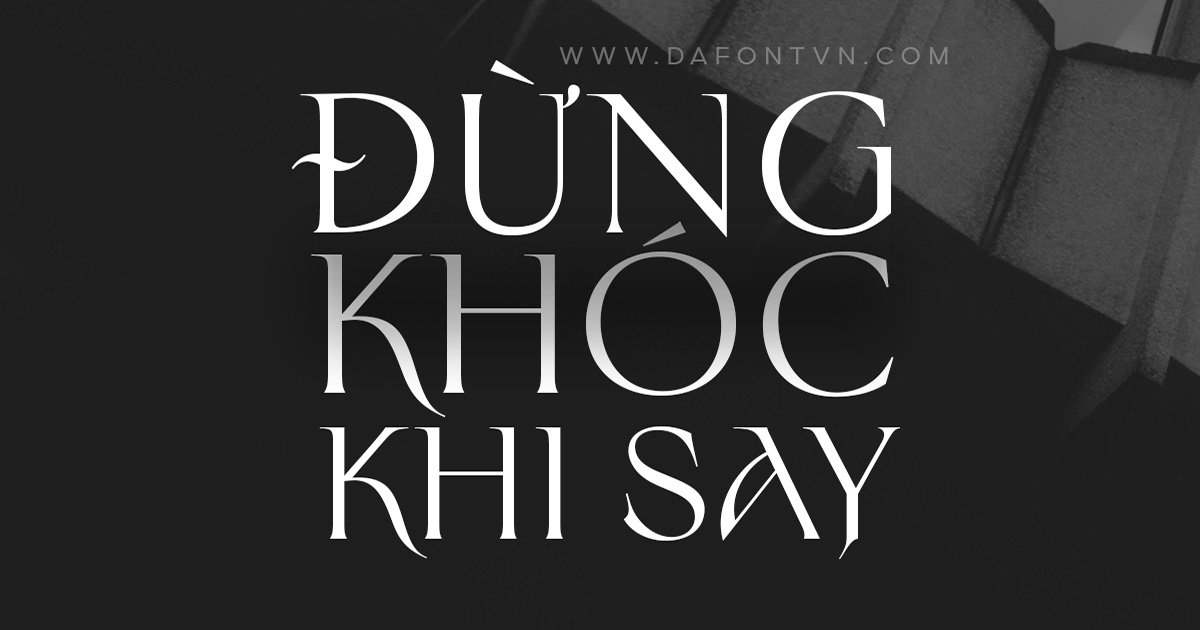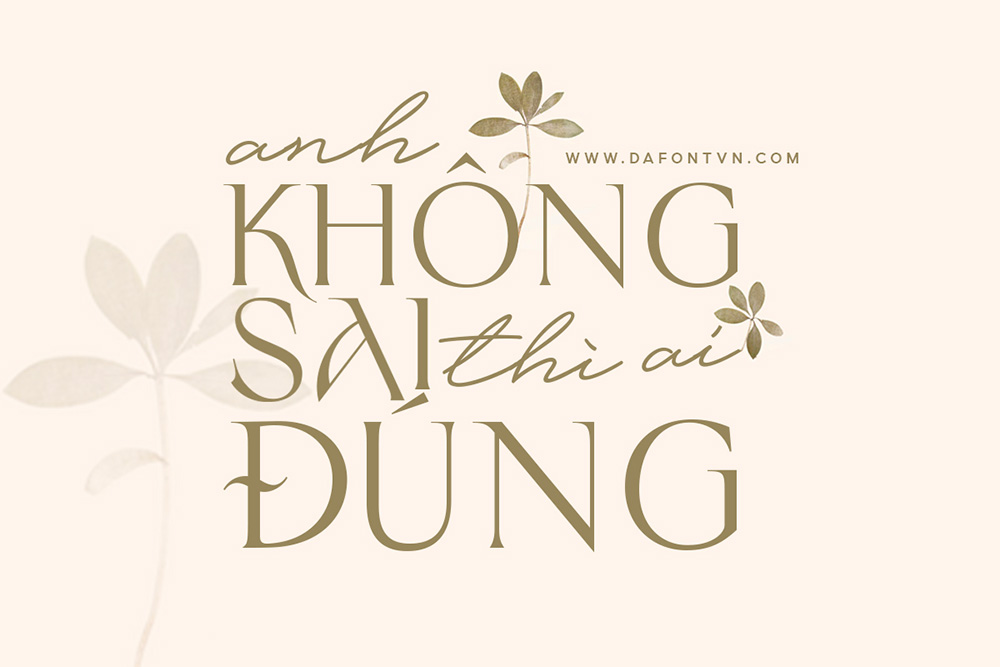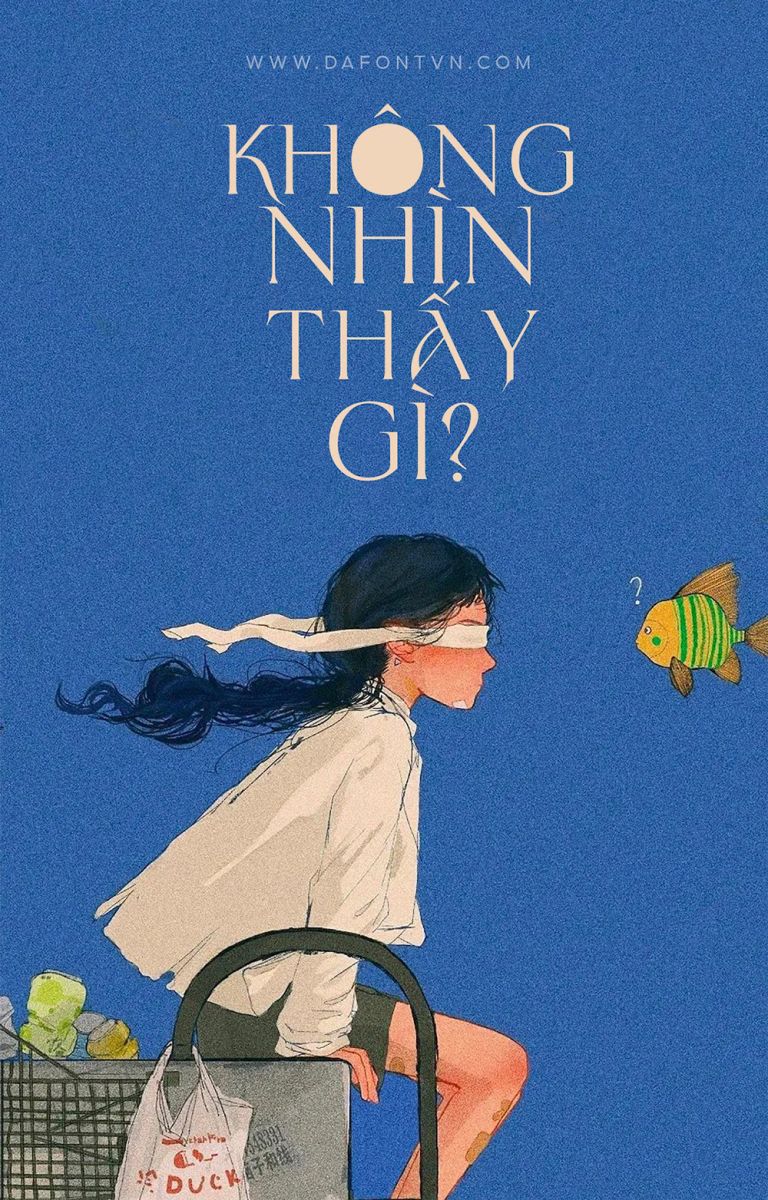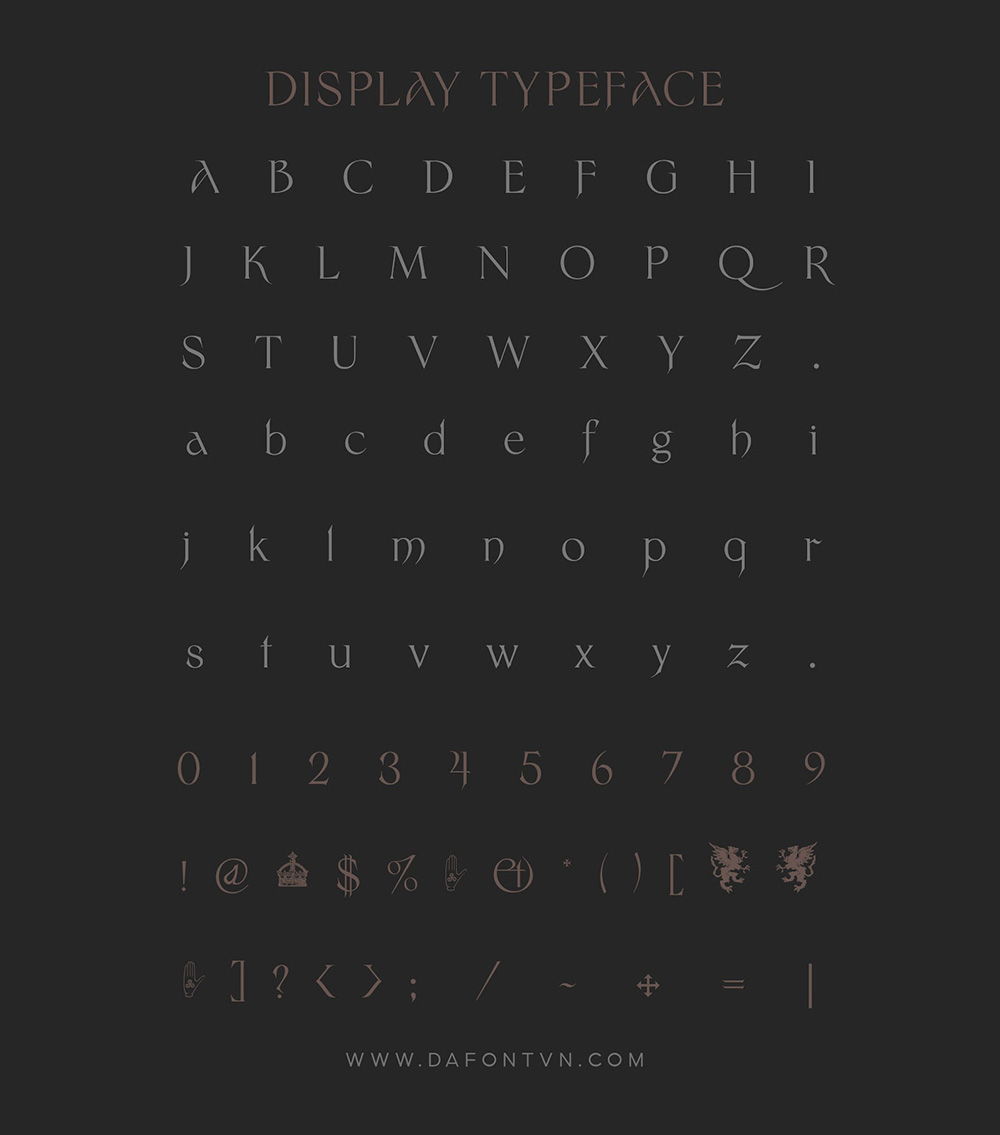
Chia Sẻ Miễn Phí Font Việt Hóa - Sinistre Cực Đẹp Mang Phong Cách Hiện Đại
Sadesign.vn vui mừng chia sẻ miễn phí font chữ Việt hóa Simple Serenity, mang đến sự kết hợp hoàn hảo giữa phong cách hiện đại và cổ điển. Được thiết kế để mang lại vẻ đẹp tối giản nhưng đầy sức hút, Simple Serenity là lựa chọn lý tưởng cho các designer yêu thích sự tinh tế và sang trọng. Với sự hỗ trợ đầy đủ các ký tự tiếng Việt, font này sẽ giúp các bạn tạo ra những sản phẩm thiết kế đẳng cấp.
1. Đặc Điểm Nổi Bật Của Font Simple Serenity
Font Simple Serenity được thiết kế với phong cách hiện đại nhưng vẫn giữ được nét cổ điển đặc trưng. Các đường nét mềm mại, thanh thoát và tỉ mỉ tạo nên một cảm giác hài hòa, dễ nhìn. Font chữ này rất phù hợp với những dự án thiết kế yêu cầu sự tinh tế và sang trọng nhưng không quá phô trương. Đặc biệt, với sự kết hợp giữa cổ điển và hiện đại, Simple Serenity có thể dễ dàng sử dụng cho các thiết kế từ các thương hiệu hiện đại đến các sản phẩm mang đậm nét cổ điển.
2. Phong Cách Việt Hóa Đầy Đủ
Một trong những điểm mạnh của Simple Serenity là khả năng hỗ trợ đầy đủ các ký tự tiếng Việt, giúp các designer dễ dàng sử dụng trong các dự án thiết kế có chứa tiếng Việt mà không lo thiếu sót. Những dấu câu như dấu sắc, huyền, hỏi, ngã… được thiết kế tinh tế, không làm mất đi tính thẩm mỹ của font chữ. Điều này tạo ra một bản thiết kế hoàn chỉnh, dễ đọc và đồng nhất.
Ứng Dụng Font Simple Serenity Trong Các Dự Án Thiết Kế
1. Thiết Kế Logo Và Thương Hiệu
Font Simple Serenity là một lựa chọn tuyệt vời cho các thiết kế logo mang phong cách hiện đại pha lẫn cổ điển. Những thương hiệu muốn tạo dựng hình ảnh thanh thoát, tinh tế nhưng không thiếu phần mạnh mẽ sẽ thấy font này là sự lựa chọn hoàn hảo.
2. Thiệp Mời Và Quảng Cáo
Simple Serenity rất thích hợp cho thiết kế thiệp mời, đặc biệt là các sự kiện mang tính trang trọng như đám cưới, hội nghị hoặc các buổi tiệc kỷ niệm. Font chữ này sẽ mang lại cảm giác lịch sự, thanh thoát nhưng không kém phần cuốn hút.
3. Thiết Kế Bao Bì Và Nhãn Mác Sản Phẩm
Sự kết hợp giữa cổ điển và hiện đại giúp font Simple Serenity dễ dàng ứng dụng trong thiết kế bao bì sản phẩm. Thiết kế bao bì với Simple Serenity sẽ giúp sản phẩm nổi bật, truyền tải thông điệp thương hiệu một cách rõ ràng, dễ dàng tiếp cận người tiêu dùng.